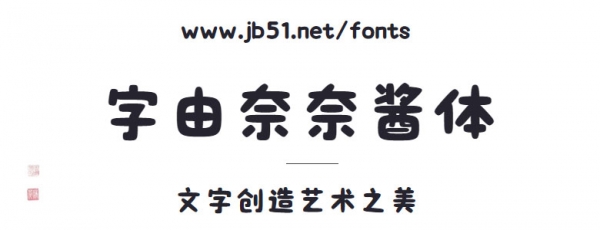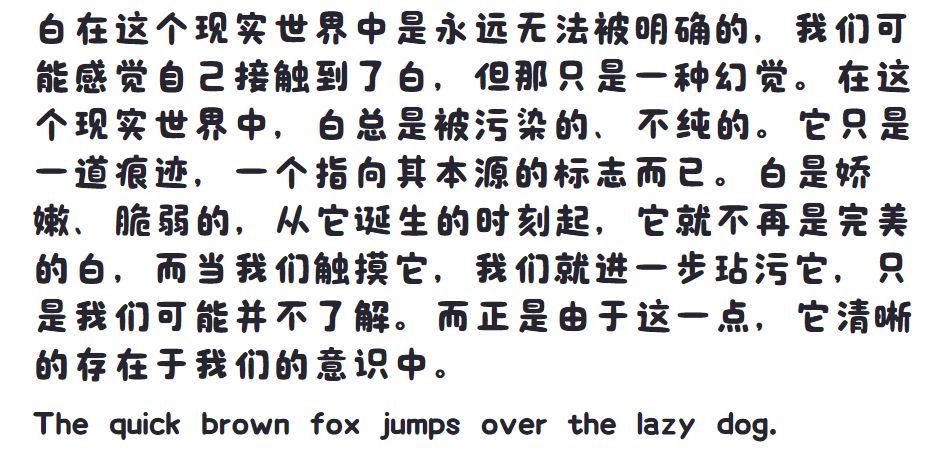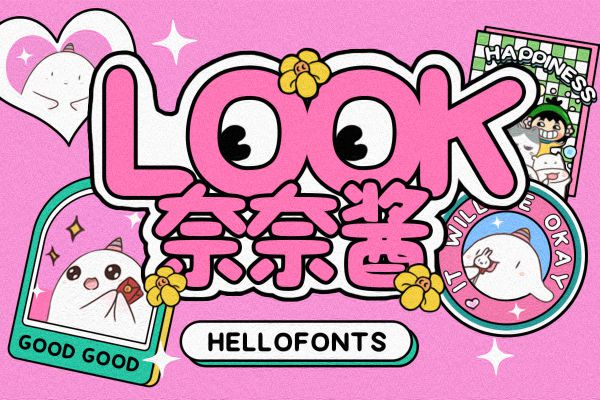
字由奈奈酱体
字由奈奈酱体是一款为IP形象“奈奈酱”量身打造的字体,这款字体饱满圆润,富有活力。结构较为洒落,不拘一格的形态具有天真浪漫之趣。与“奈奈酱”天真可爱的外表相呼应。笔画行笔流畅、转折顺滑,有着手写带来的自然弧度感,提高了字体的可读性和亲切感。大大贴合了“奈奈酱”憨态可掬的内在特征。略显拙稚的字体线条,宽松疏朗的字形内白,让字体和“奈奈酱”完美的结合在了一起。
字体介绍
风格
温和亲切 / 有趣/卡通/创意字体
字体应用示例